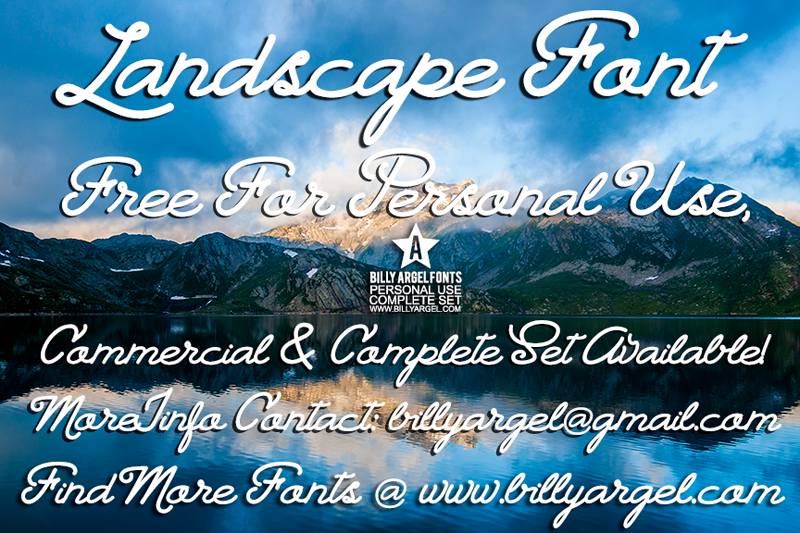
Landscape Font – Download Grátis
A Landscape Font é uma mão-dura e autêntica, criada pelo designer Hamilton para aqueles que adoram incorporar um toque artesanal a seus projetos digitais. Com suas linhas suaves e detalhes delicados, esta fonte é perfeita para quem busca algo mais pessoal em seu trabalho gráfico. Esse conjunto de caracteres escritos à mão se destaca por sua versatilidade, oferecendo uma sensação natural que se combina bem com vários estilos. Suas linhas fluidas e texturas únicas são ideais para criar designs que transmitem emoção semelhante a um desenho feito à mão. Ideal tanto para trabalhos pessoais quanto para projetos comerciais, esta fonte é uma ótima escolha para quem busca adicionar mais personalidade aos seus documentos e design gráfico. A Hamilton também disponibiliza informações adicionais sobre como obter permissões de licenciamento comerciais e um acesso direto ao site oficial. Visite o site www.billyargel.com e explore mais trabalhos do designer, onde você pode encontrá-lo em seu perfil na Facebook, www.facebook.com/billyargelfonts. A Landscape Font é uma adição indispensável para qualquer coleção de fontes escritas à mão.